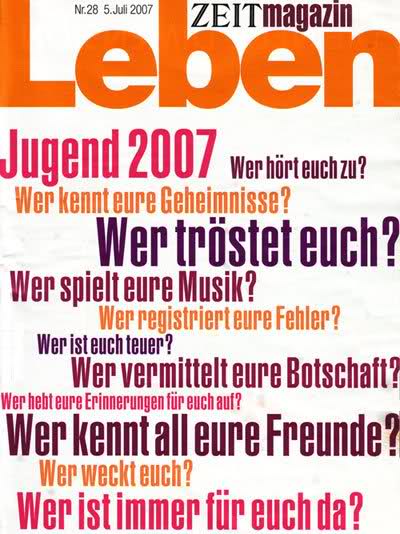
Schriftart Zeit Magazin
ich brauch mal wieder eure hilfe. diesmal ist es sogar besonders schwierig, weil ich kein bild dazu finde.
und zwar suche ich die schriftart, die im zeit magazin, der beilage der wochenzeitung, für unterüberschriften und seitenzahlen u.ä. verwendet wird.
könnte das diese hier sein? hab gerade keine zur Hand:
tut mir leid, ich meine nicht fließtexte und überschriften, sondern die unterüberschriften im magazin. sorry, ich hab schon gegoogelt aber kein bild dazu gefunden. die schrift erinnert mich an die »Luxury Gold« von House Industries, bin mir aber keineswegs sicher.
Ich hatte schon länger kein Exemplar mehr in den Händen – aber nach dem Relaunch kamen zahlreiche Helvetica-Varianten, insbesondere die fette und ultra-kompresse, zum Einsatz. Aber ohne Beispiel ist das wirklich etwas schwierig …
Aber ohne Beispiel ist das wirklich etwas schwierig …
richtig, ich werde nächste woche ein exemplar einscannen und ein sample online stellen, trotzdem schon ganz dick dankeschön und bis bald in diesem thread :)
Wann war eigentlich dieser Tapetenwechsel bei der Zeit? Ich habe hier eine Zeit vom Juli 2001 liegen, die ich im Kaminofen verfeuere. :hammer:
Meine Mutter hat die gehortet.
Aber da waren die auch schon mit der breiten Helvetica, Garamond und Tiemann unterwegs. Oder haben die aktuell ein neues Schriftbild? Lange keine mehr in den Händen gehabt. Wieso auch, hab ja noch einen Stapel davon :mrgreen: